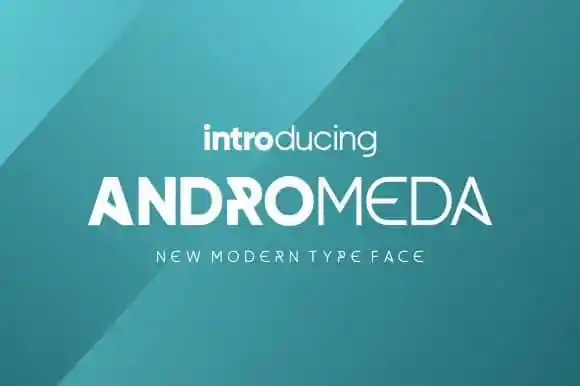
Andromeda Display Font – Download Grátis
A Andromeda Display é uma elegante fonte futurista que combina características marcantes para logos tecnológicos e marcas fortes. Ideal para aplicar em posters, camisetas, embalagens, marca, logotipo e mais. Criada pelo CreativeKiller, esta tipografia vem em dois pesos distintos. Seu ar saudável e moderno se adapta perfeitamente a qualquer tipo de mensagem, transmitindo confiança e estilo. Perfeita para criar um design visual impactante que destacará seu trabalho nas mídias sociais ou no ambiente digital. Seja você uma marca querendo estabelecer sua presença online ou alguém criando materiais publicitários, a Andromeda Display é uma escolha ótima para dar vida à sua criação de design.